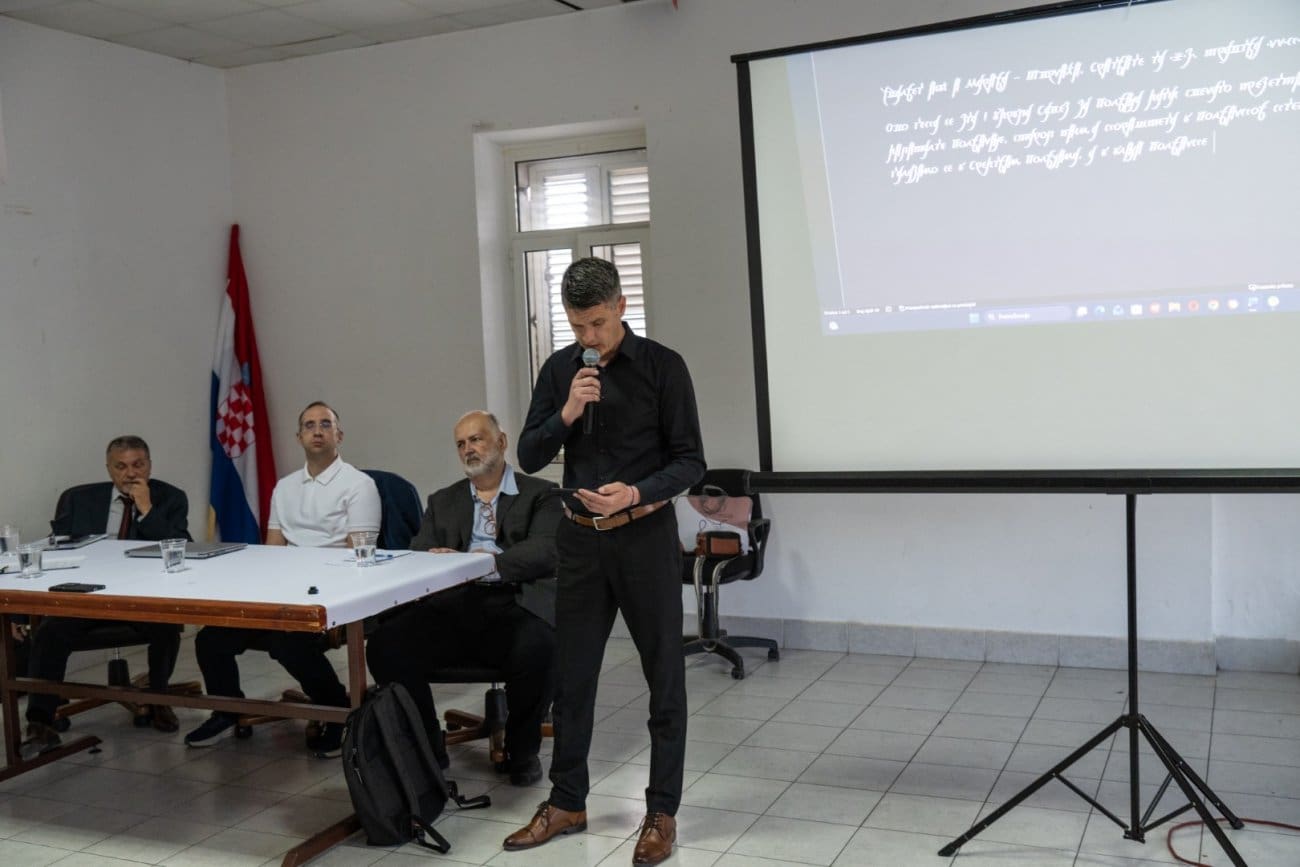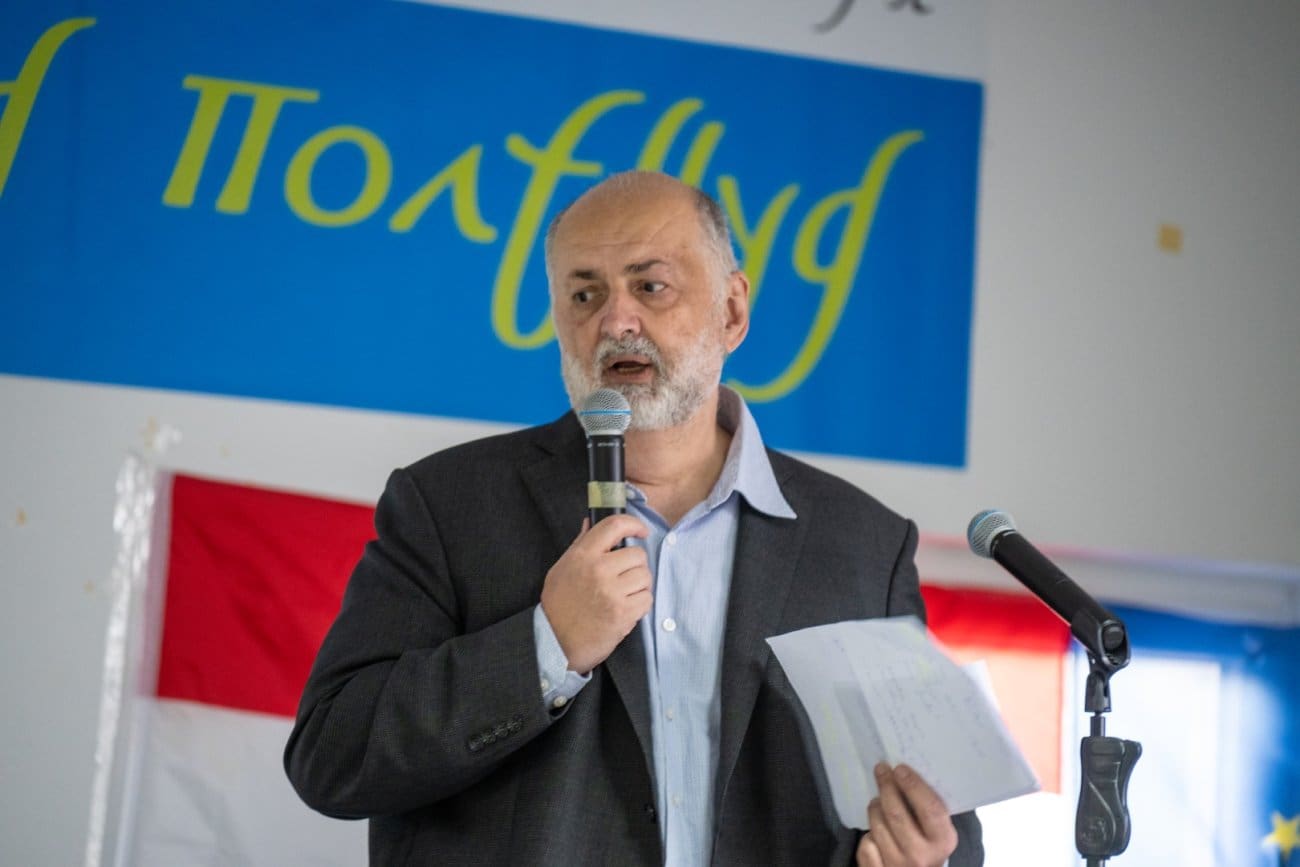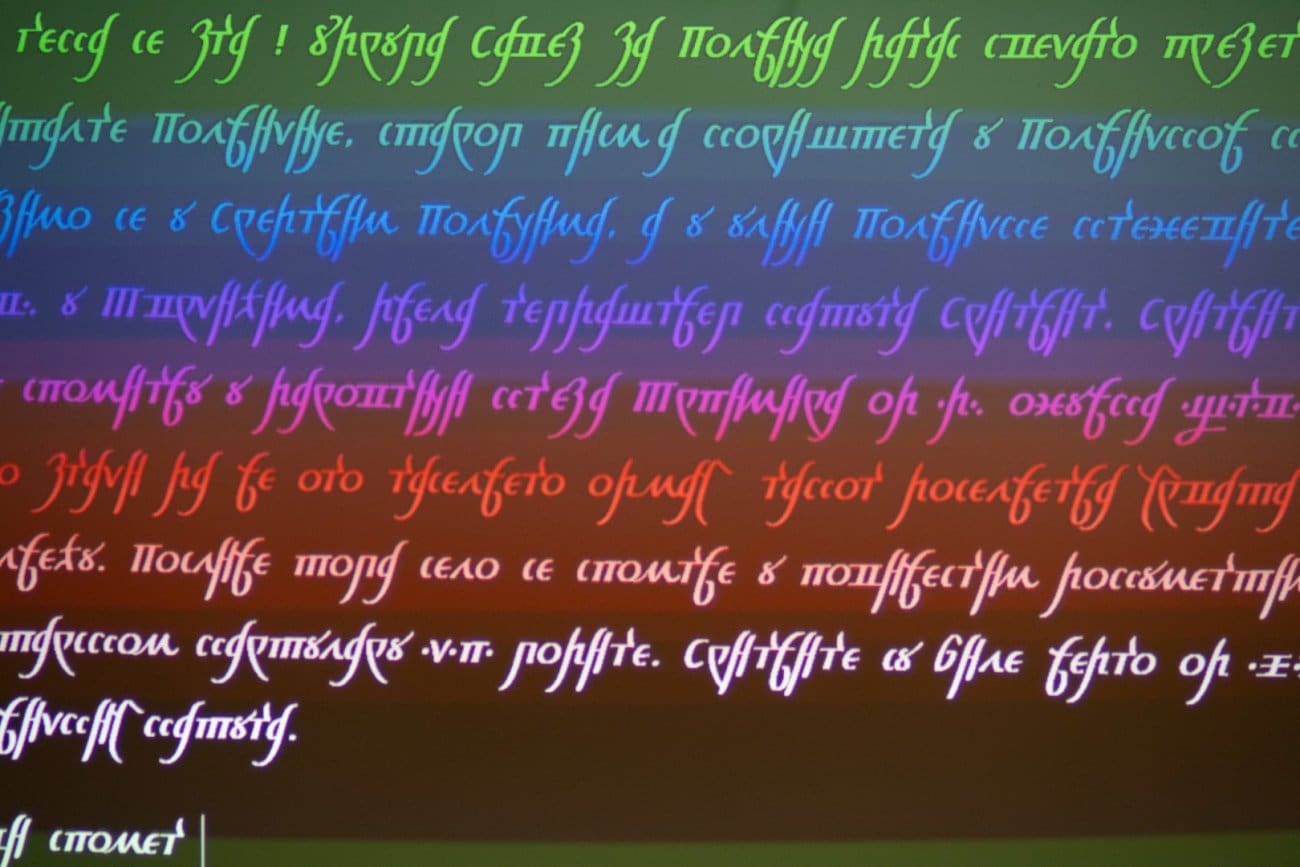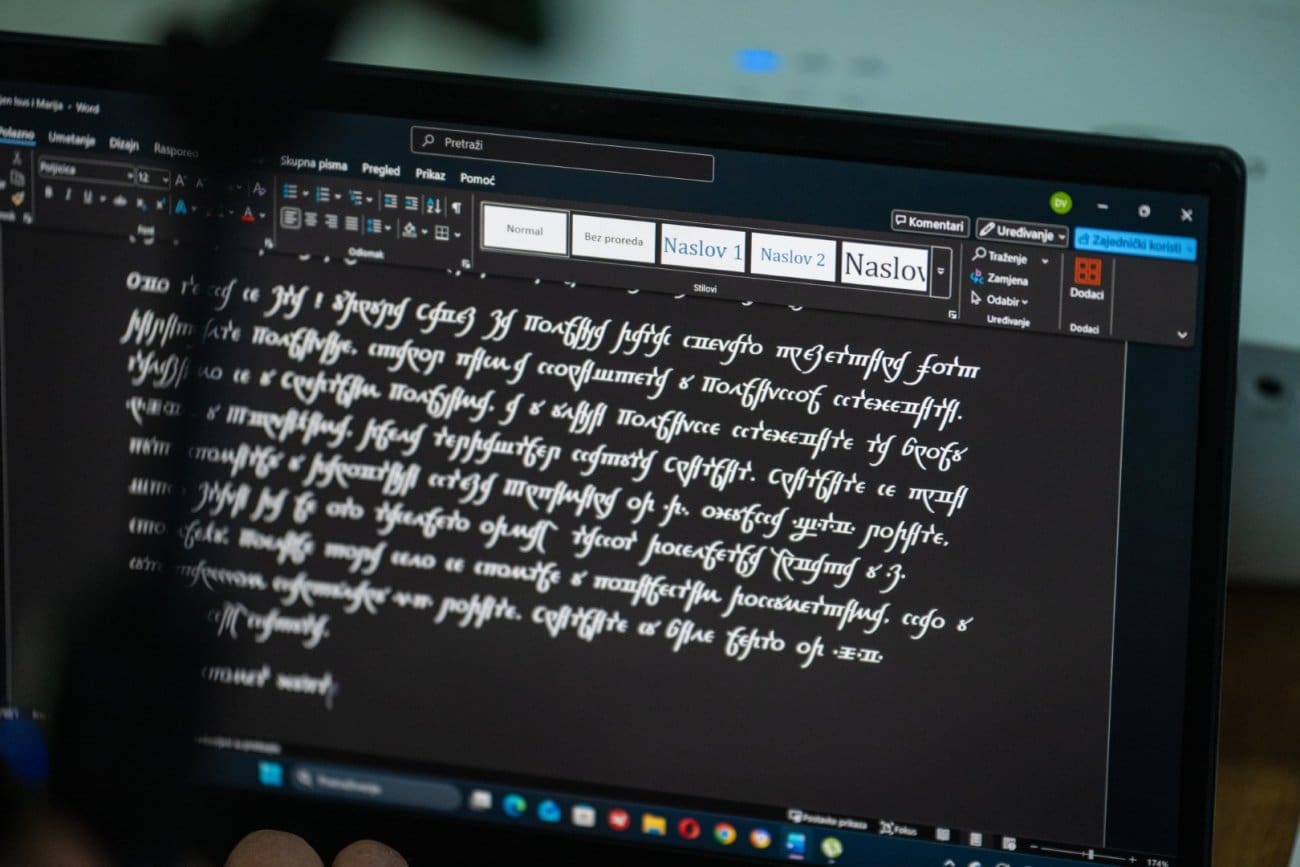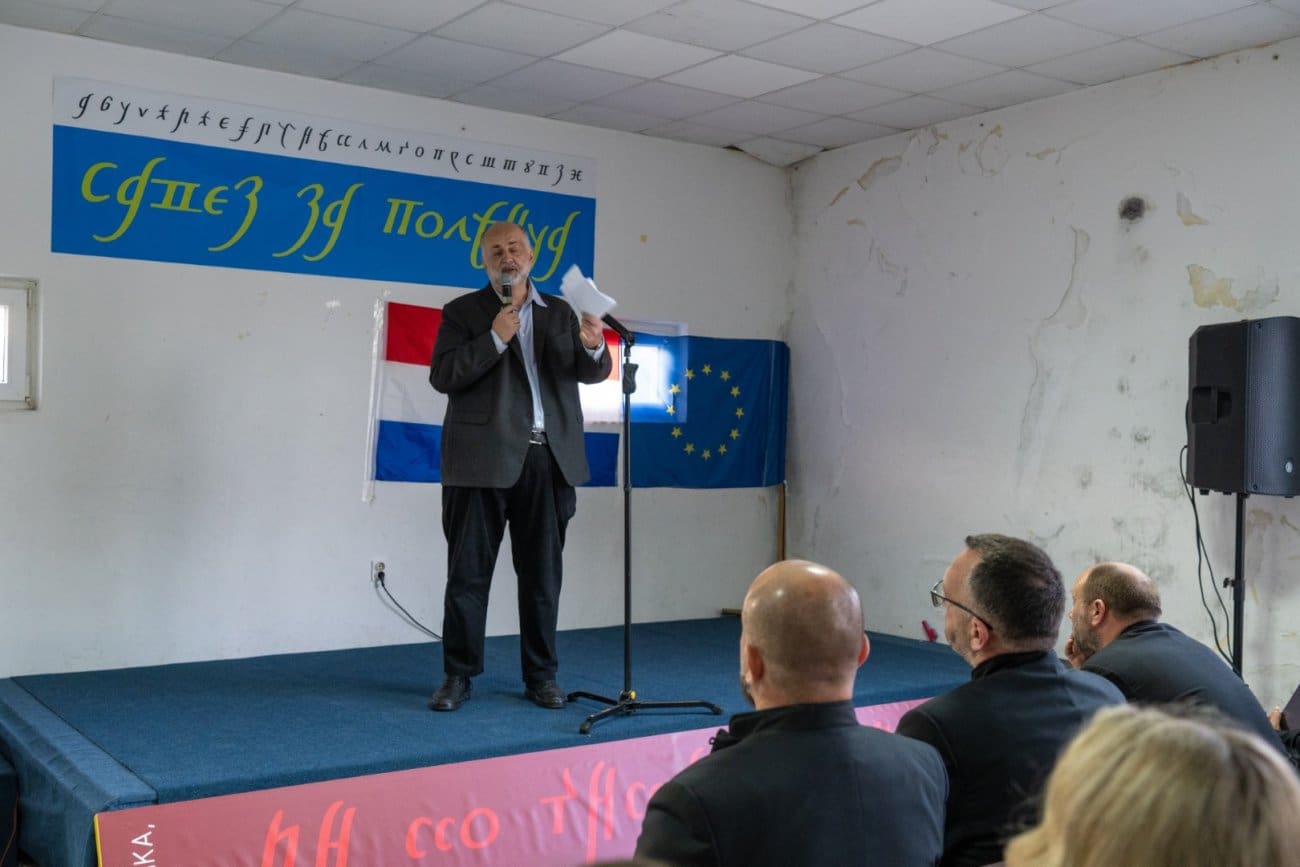
OVO ĆE ODJEKNUTI Poljičica dobila digitalni font, inspiriran je Poljičkim statutom! "Mladi će biti oduševljeni kada isprobaju na mobitelu..."
[FOTO + VIDEO] Poljičica dobila digitalni život: Emotivna večer u Srinjinama pokazala da baština Poljica ima budućnost
U Domu kulture u Tvrčićima, u Srinjinama, u petak navečer održana je svečanost predstavljanja digitalnog fonta “Poljičica” – projekta koji na suvremen način oživljava jedno od najvažnijih obilježja poljičke kulturne baštine.
Riječ je o važnom iskoraku u očuvanju pisma koje je 2023. godine proglašeno nematerijalnim kulturnim dobrom Republike Hrvatske, a večer u Srinjinama potvrdila je koliko je poljičica i danas snažan simbol identiteta i ponosa ovog kraja.
“Ovo je važan korak za očuvanje svijesti našeg naroda”
Okupljenima se na početku obratio predsjednik Saveza za Poljica Duško Karaman, naglasivši važnost projekta:
– Danas, nepune tri godine nakon što je poljičica proglašena kulturnim dobrom, radimo novi korak – a to je digitalni ispis. Ovo je važan korak za očuvanje svijesti našeg naroda – poručio je.
U ime Grada Omiša okupljene je pozdravio dogradonačelnik Ivan Pivčević, istaknuvši kako poljičica nadilazi svoju osnovnu funkciju pisma.
– To nije samo sredstvo zapisivanja riječi, nego i snažan simbol identiteta, povijesti i ponosa poljičkog kraja – rekao je, dodavši da digitalizacija omogućuje da ovo vrijedno nasljeđe ponovno zaživi u obrazovanju, komunikaciji i suvremenom stvaralaštvu.
Posebno je naglasio važnost uključivanja mladih:
– Upravo mlade generacije pokazuju interes i kreativnost u oživljavanju ove baštine. To nam daje sigurnost da poljičica neće ostati samo dio povijesti, nego i dio naše budućnosti.
Pismo koje povezuje Poljica sa širim slavenskim svijetom
U stručnom dijelu programa istaknuto je kako poljičica nije izolirani fenomen, već dio šire kulturne i povijesne slike. Naglašeno je da se radi o specifičnom obliku hrvatske ćirilice koji se razvio na prostoru Poljica, ali i šire, te da nosi posebnosti koje ga čine jedinstvenim u zapadnom kulturnom krugu.
Poljičica je tako još jednom predstavljena ne samo kao lokalna vrijednost, nego kao dio šire europske i slavenske kulturne baštine. Predstavljanje digitalnog fonta otkrilo je i zahtjevnost procesa njegove izrade. Projekt je uključivao analizu brojnih povijesnih izvora i dokumenata, a svaki znak pomno je oblikovan kako bi zadržao autentičnost, ali i funkcionalnost u suvremenom digitalnom okruženju.